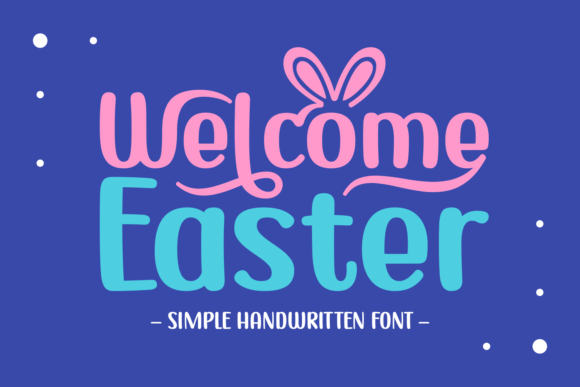
Welcome Easter
Пошук відповідних елементів дизайну може бути складним, але Welcome Easter пропонує виняткову колекцію, яка миттєво покращить вашу роботу.
Створений з високою точністю, Welcome Easter забезпечує чисті вектори, плавну типографіку та комерційну ліцензію для вашого спокою.
Незалежно від того, чи створюєте ви продукти POD (друк на вимогу), весільні запрошення або графіку для соціальних мереж, Welcome Easter стане ідеальним вибором.